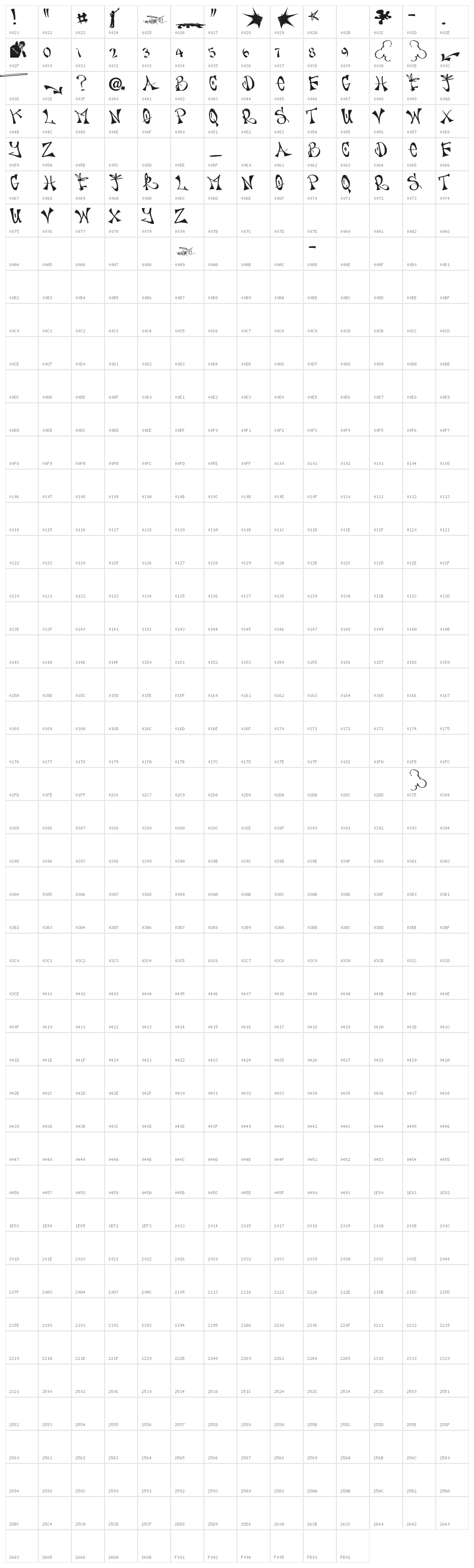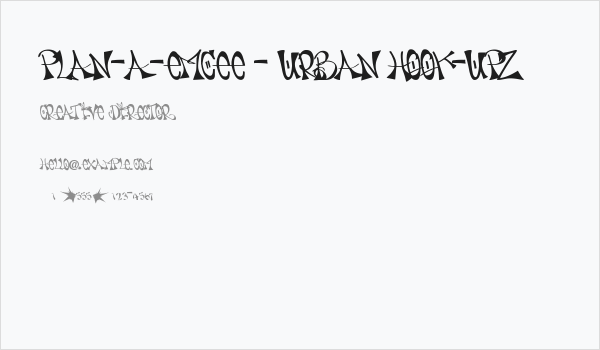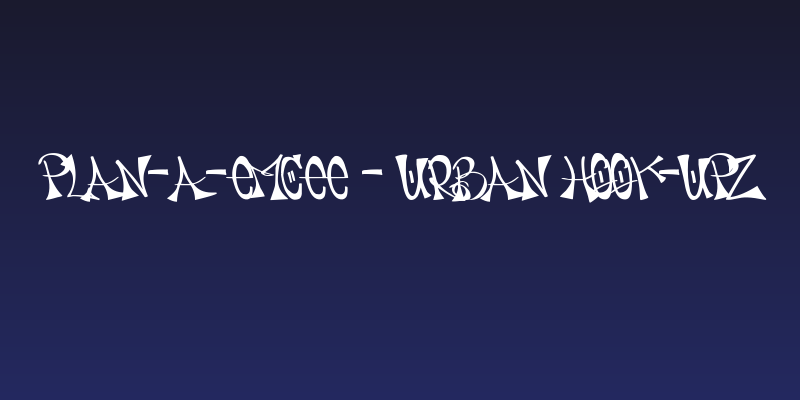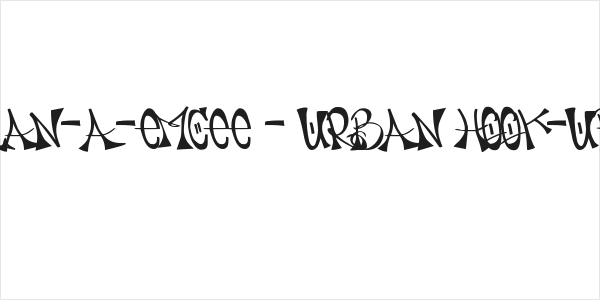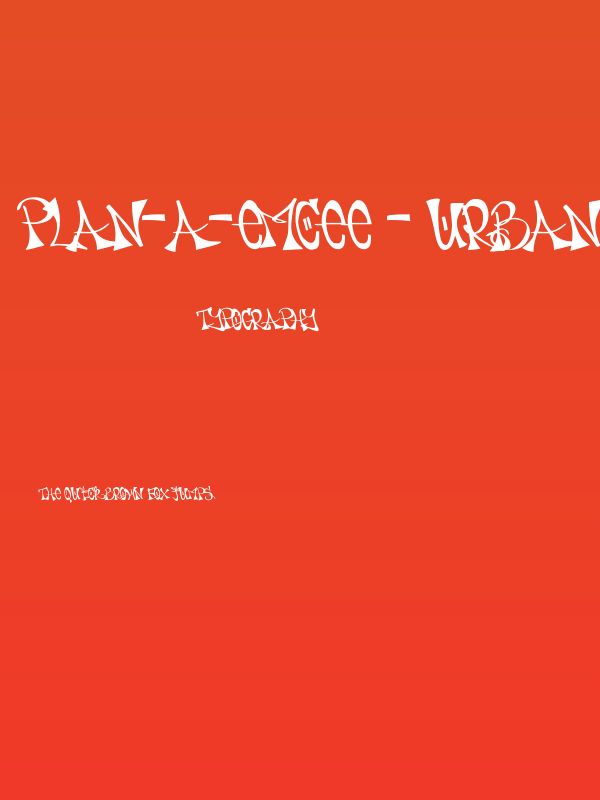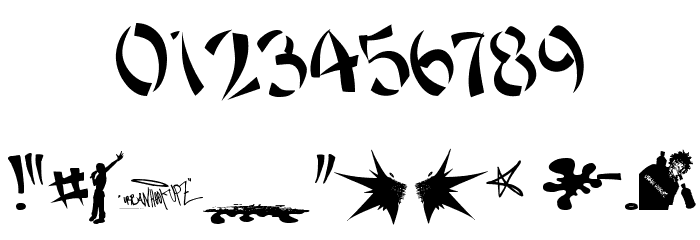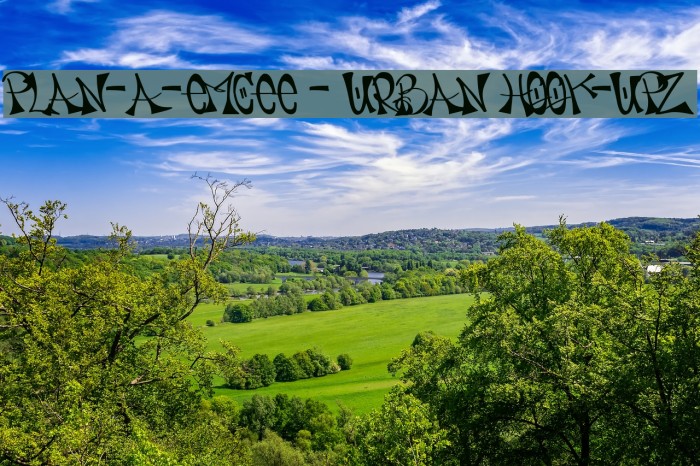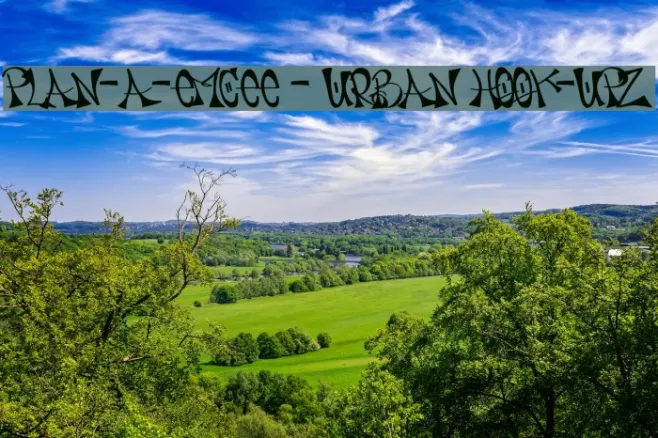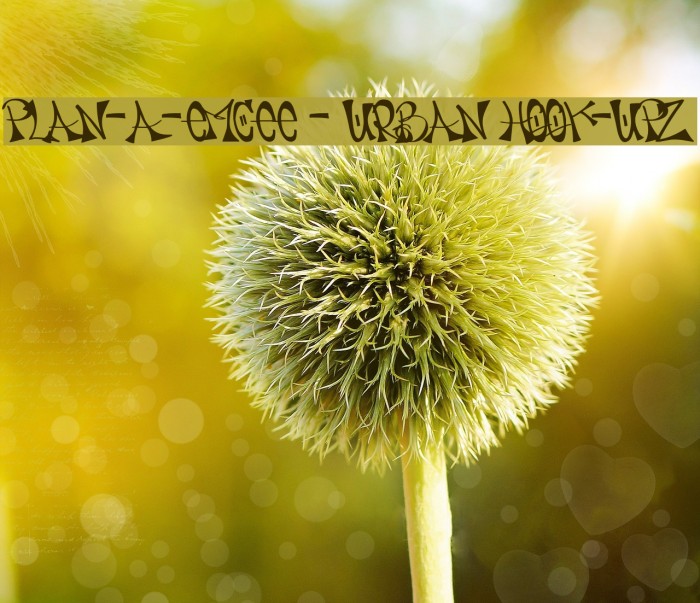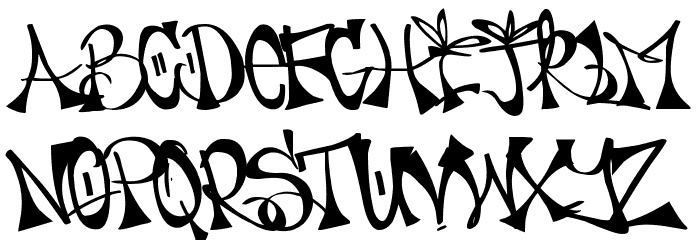
PLAN-A-EMCEE - URBAN HOOK-UPZ Font
| Style général | Urban, Graffiti, Edgy |
| Projets proposés | Ideal for street art projects, urban-themed designs, music album covers, and event posters. |